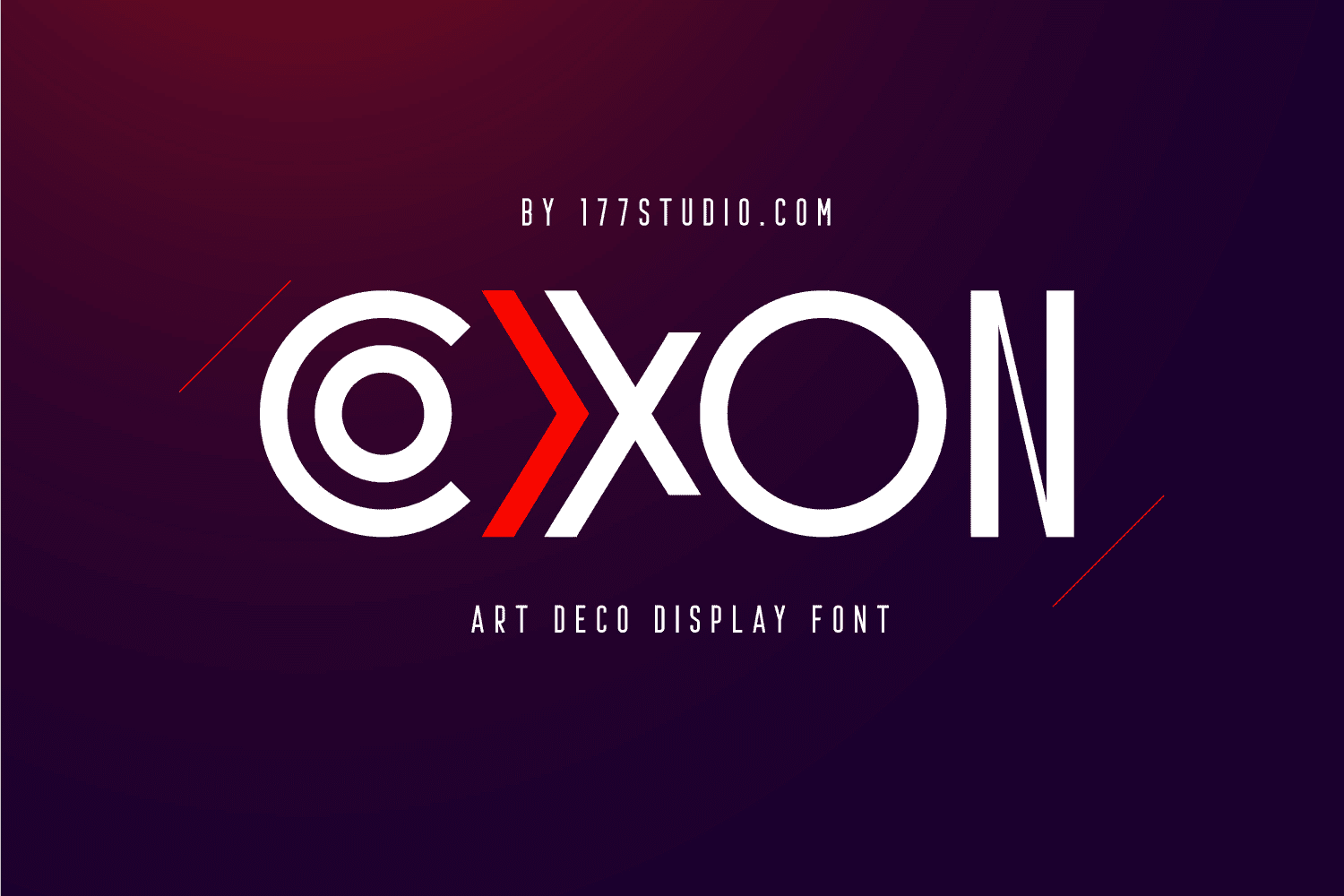
[Creativefabrica] Coxxon Font (2021)
Coxxon
- это крутой, современный и смелый шрифт.
Повеселитесь с этим красивым шрифтом и исследуйте его бесконечные вариации.